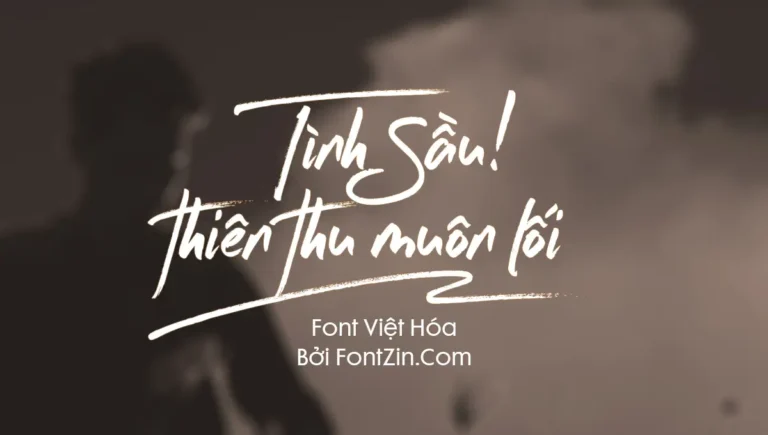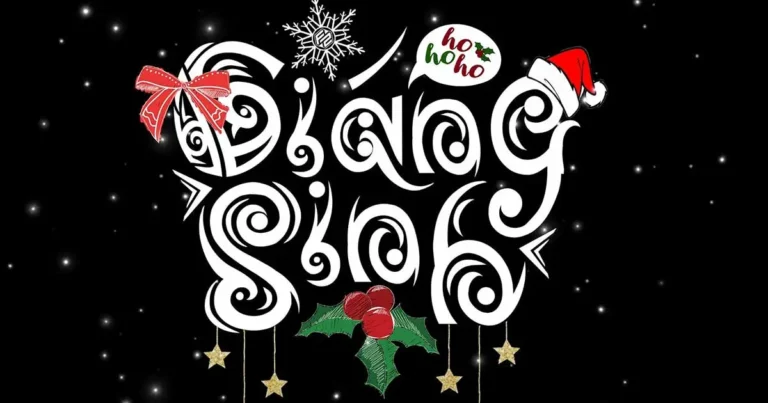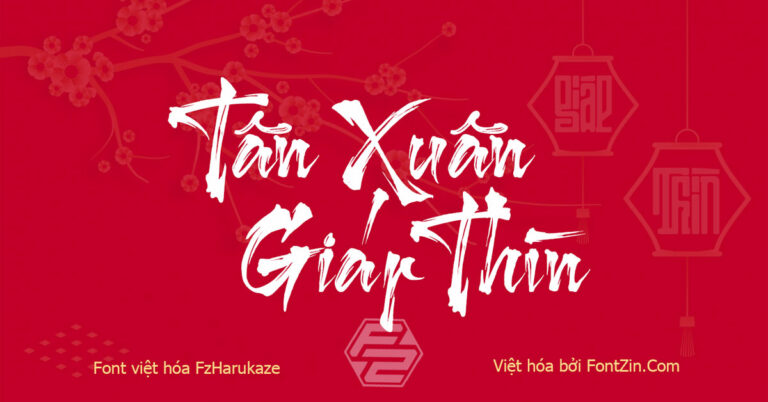
Hi bạn! Có thể đã nghe nói hoặc mới chỉ khám phá FontZin Team, nhưng chắc chắn bạn đến đây để ủng hộ, tương tác và tìm kiếm những tài nguyên thiết kế tuyệt vời. FontZin suốt 3 năm qua đã chia sẻ nhiều nguồn tài nguyên đặc biệt là font tiếng việt có hơn 200 font chữ đã được chúng tôi Việt hóa. Rất vui được giới thiệu với bạn, bộ sưu tập 200+ font việt hóa bởi FontZin bên dưới nhé!
Font Việt hóa là gì? Có nên sử dụng không?
Trước khi đi vào giới thiệu danh sách các font bên mình đã Việt hóa và chia sẻ đến cộng đồng thì có 2 câu hỏi trên cần làm rõ để bạn hiểu hơn về mục đích của bài viết này.
Font Việt hóa là gì?
“Font Việt hóa” là thuật ngữ được sử dụng để mô tả các font chữ được chuyển đổi từ font chữ nguyên gốc (thường là font chữ nước ngoài) sang font chữ hỗ trợ tiếng Việt. Quá trình này bao gồm việc thêm các ký tự và dấu tiếng Việt vào font gốc để phục vụ cho việc hiển thị tiếng Việt.
Font Việt hóa thường được sử dụng để hiển thị văn bản tiếng Việt một cách chính xác và đẹp mắt trên máy tính, trang web, hoặc trong các ứng dụng khác. Việc này giúp đảm bảo rằng các ký tự tiếng Việt và dấu diacritical (như dấu chấm, dấu hỏi, dấu ngã, v.v.) được hiển thị đúng cách và không gặp vấn đề về kiểu chữ.
Có nên sử dụng Font chữ đã Việt hóa không?
Việc sử dụng font chữ đã Việt hóa có những lợi ích cụ thể, tùy thuộc vào mục đích sử dụng và yêu cầu cụ thể của bạn:
- Hỗ trợ Tiếng Việt: Font chữ Việt hóa được tối ưu hóa để hiển thị tiếng Việt đúng cách với các dấu diacritical (dấu chấm, dấu hỏi, dấu ngã, v.v.). Điều này giúp đảm bảo văn bản của bạn sẽ được hiển thị chính xác và đẹp mắt.
- Thích hợp cho Thiết kế Đồ họa: Nếu bạn đang thực hiện thiết kế đồ họa cho các dự án tiếng Việt, việc sử dụng font chữ đã Việt hóa có thể giúp tạo ra giao diện hoặc nội dung văn bản thích hợp với người đọc địa phương.
- Tương thích và Giao tiếp tốt hơn: Nếu bạn chia sẻ tài liệu hoặc trang web của mình với người đọc tiếng Việt, sử dụng font chữ Việt hóa giúp đảm bảo rằng mọi người có thể đọc và hiểu nội dung một cách thuận tiện.
Cuối cùng, quyết định sử dụng font chữ nào phụ thuộc vào mục đích cụ thể của bạn và yêu cầu thiết kế.
10 Font Việt hóa đẹp, hiện đại dùng thiết kế thời trang, quảng cáo, banner.
Font Serif là lựa chọn hàng đầu cho các thiết kế mang khuynh hướng hiện đại, dưới đây là 10 font điển hình mà FontZin muốn giới thiệu đến bạn.Font Serif Việt Hóa đẹp Druzhok
Phong cách thiết kế độc đáo, sáng tạo, tinh tế và rất hiện đại, miễn phí cho thương mại và cá nhân theo giấy phép Creative Commons.
Font serif việt hóa Nyght đậm chất cổ điển và thanh lịch
Bộ phông chữ này là sự kết hợp hoàn hảo giữa đường cong mềm mại và nét sắc nhọn của serif, dấu tiếng Việt thiết kế đẹp, chuẩn.
Font Chữ Đẹp Pearl Blossom
Là Phông chữ Serif hiện đại, thiết kế với phong cách độc đáo, nhiều kí tự đặc biệt thay thế đẹp.
Font chữ đẹp Futura maxi
Futura maxi là một trong những bộ font chữ nổi tiếng của nhà phát hành Monotype. Với thiết kế chuẩn hình học; các nét chữ tròn, vuông, cao độ thấp.
Font Việt hóa Georgia Ballpark
Bộ font này kết hợp giữa Font Serif tân thời và Script Viết tay, 2 phông chữ này sinh ra là để cho nhau
Bộ Font Việt Hóa Canela 12Style
Bộ 12style font việt hóa Canela được phát hành bởi commercialtype. Font hỗ trợ sẵn Tiếng Việt nên bạn yên tâm về sự đồng nhất trong font
Quagera Font chữ Việt hóa siêu đẹp
Phông chữ này được cách điệu với các nét uốn lượn đầy cá tính và rất hiện đại, Kiểu chữ đẹp độc lạ.
Font chữ đẹp việt hóa Milans
1 siêu phẩm dạng serif, thiết kế sang trọng, phong cách hiện đại, Hãy tải ngay phông chữ miễn phí này.
Font Astila Việt Hóa 257 Glyphs
Font Astila được thiết kế nhiều ký tự thay thế sử dụng linh hoạt, các nét chữ mềm, bo tròn kế thừa phong cách hiện đại và cổ điển.
34 Sài Gòn Xưa có phong cách dấu tiếng Việt kiểu bao cấp.
Dưới đây là danh sách các font chữ được Việt hóa với bộ dấu mang phong cách hoài cổ, kiểu dấu thời bao cấp thường được thấy tạp chí cũ, sách báo xưa và các biển quảng cáo trên phó Sài gòn Xưa.20 Font Hoài Cổ Sài Gòn Xưa Việt Hóa bởi admin Thái Hiếu
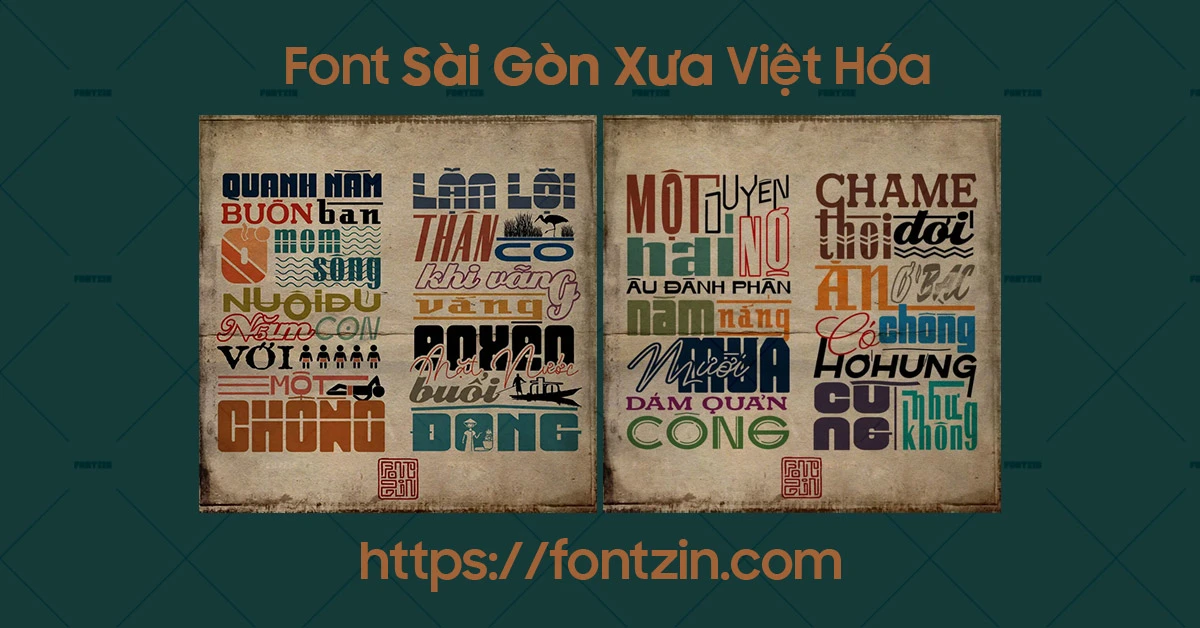
Bộ 20 Font hoài cổ Việt hóa Miễn phí, Đây là một trong những dự án về Font sài gòn xưa của FontZin được cộng đồng đón nhận và đánh giá cao.
10 Font Sài Gòn Xưa thiết kế bởi Thái Hiếu miễn phí Thương Mại 100%
Free 10 Font sài gòn xưa đẹp các nét chữ, dấu tiếng Việt, vị trí sắp xếp dấu… như trên biển hiệu quảng cáo thời xưa thiết kế bởi Thái Hiếu
Font Việt Hóa Xưa Bộ 2 Phông Hoài Cổ
Gồm Script và Display, 2 phông này rất đẹp dấu tiếng Việt theo phong cánh hoài cổ, thích hợp thiết kế các chủ đề truyền thống.
2 Font Tiếng Việt Đẹp Kiểu Dấu Sài Gòn Xưa
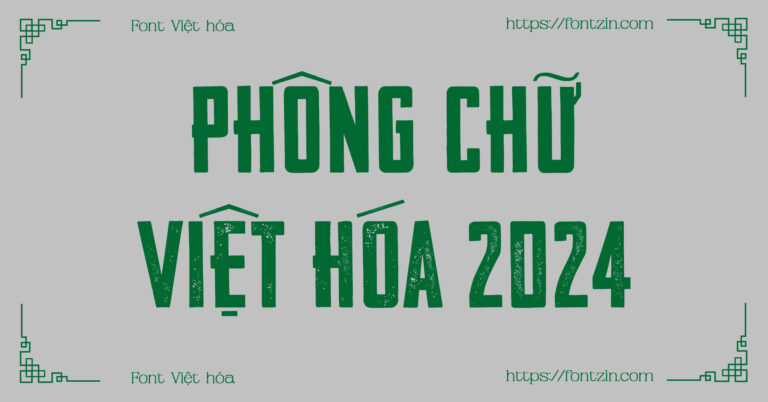
Tổng kết.
Sau 3 năm hoạt động về lĩnh vực Việt hóa và Thiết kế font, FontZin nhận thấy cộng đồng thiết kế đồ họa nói riêng và cộng đồng người Việt nói chung rất cần những bộ font được Việt hóa chuẩn dấu, chuẩn phong cách và đảm bảo được kerning đầy đủ. Với tiêu chí chuẩn, đẹp, độc, lạ, mới và miễn phí fontzin đã không ngừng nâng cao tay nghề và lựa chọn những bộ font hợp lý, miễn phí để Việt hóa chia sẻ tới cộng đồng.
Trên đây là những bộ font tâm huyết mà team muốn chia sẻ với bạn, hi vọng bạn sử dụng đúng mục đích và có nhiều thiết kế độc đáo, sáng tạo.